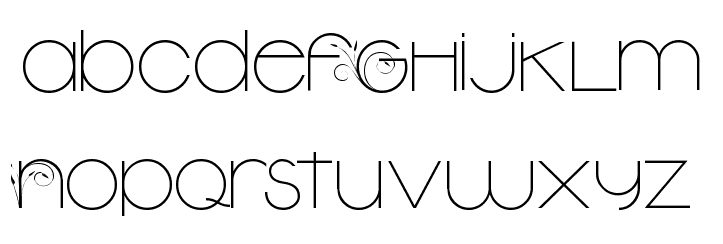
Schriftart ähnlich Camellia nicht zu finden
ich suche schon länger erfolglos und frustriert diese Schriftart s.u.
Sie hat etwas Ähnlichkeit mit Camellia EF und noch entfernter mit Circulus (nur von e und f her). Die Blumen an den n's hat die vorherige Designerin vermutlich selbst immer angefügt.
Die Schrift ist echt schwer zu finden, ich habe wirklich lange und intensiv gesucht (auf alle Arten, meine ich).
Wie hast Du die gefunden? Ich habe zig Stunden gesucht per Bild und Typo-Suchmaschinen, per Kategorien, per Ausschlussverfahren über zig Anbieter...
Mit den Schriften am Ende wirst Du sicher rechthaben (wer sie verwenden darf). Aber wenn Du erstmal stundenlang die Schrift gesucht hast, weil jemand weder erreichbar ist noch helfen will, dann ist es echt nervend. Ich wollte ihr ja nichtmal einen (ähh insg. fünf) möglichen Job wegnehmen.
Sie hätte auch selbst entsprechende Änderungen an meinen Arbeitsdateien machen können und das Finishing, wenn sie ok wäre. Es war ja ihr Design...
Datenübergabe:
Juristisch ist das sicher klar. Aber praktisch macht eine Fixierung auf das Gesetz so eng keinen Sinn mehr mMn. Schon lange finde ich das schwach.
Ich sehe es so: Gebe den Kunden die Dateien, die sie brauchen, um Print- und Onlinemedien selbst gestalten zu können und lass es sie auch tun.Sie kommen wieder, weil es immer so ist. - Auch im klassischen Handwerk, Reparaturbetrieb, Finanzberatung, etc. und so weiter...
… Wie hast Du die gefunden? Ich habe zig Stunden gesucht per Bild und Typo-Suchmaschinen, per Kategorien, per Ausschlussverfahren über zig Anbieter …